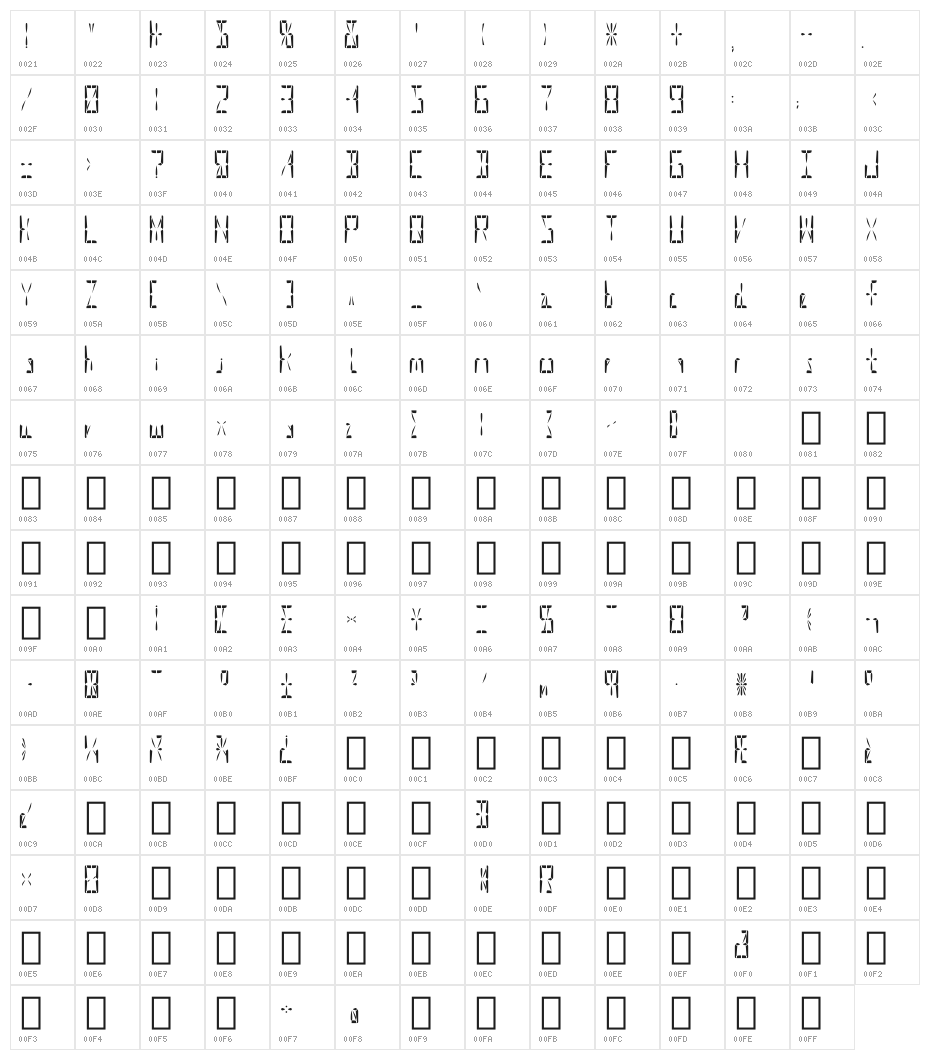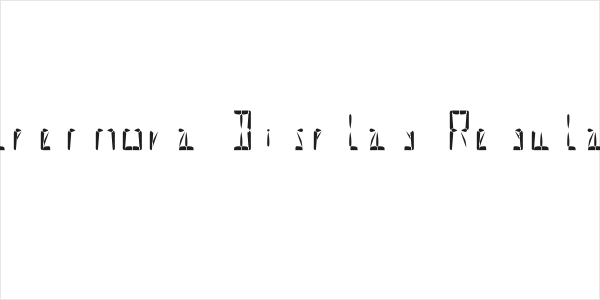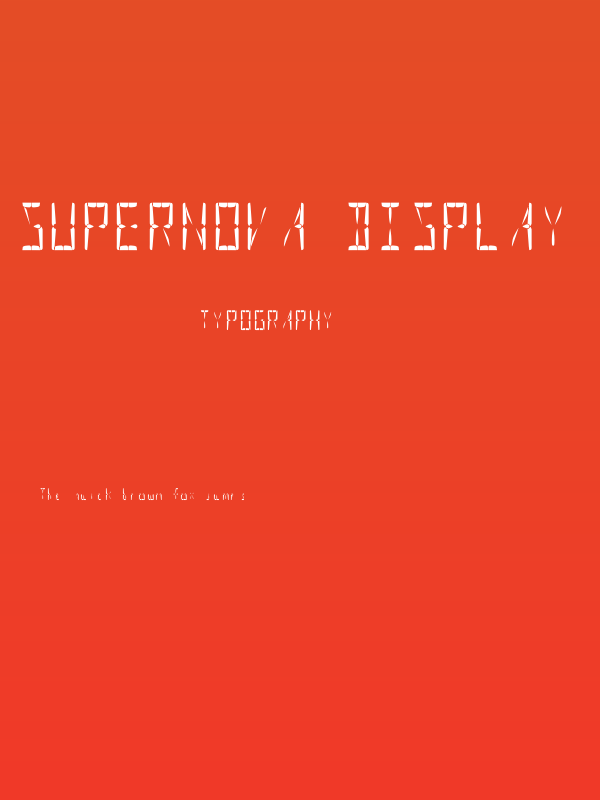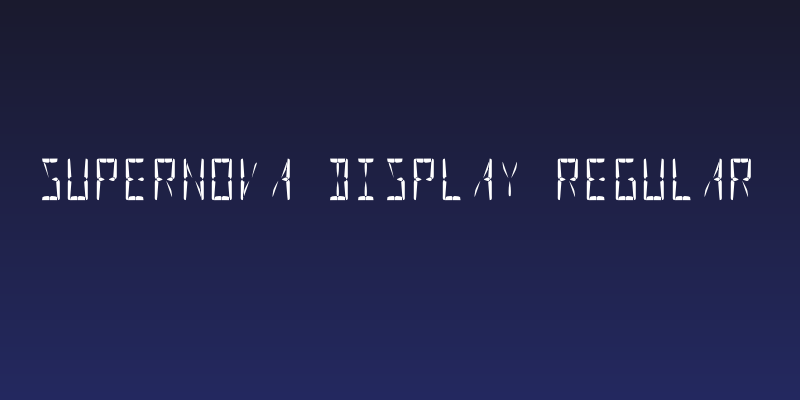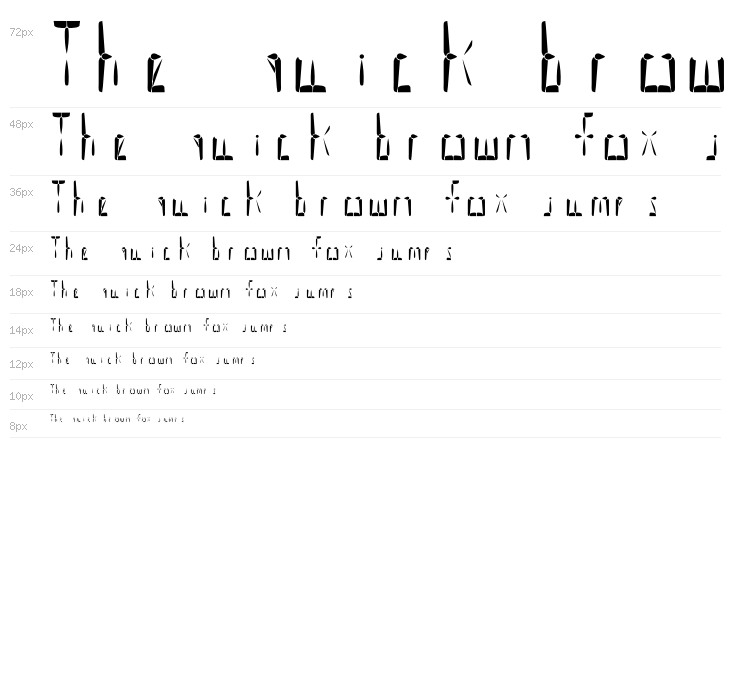
Supernova Display Regular Font
| Vorgeschlagene Projekte | Ideal for sci-fi themed designs, digital displays, posters, and branding that requires a modern and striking look. |